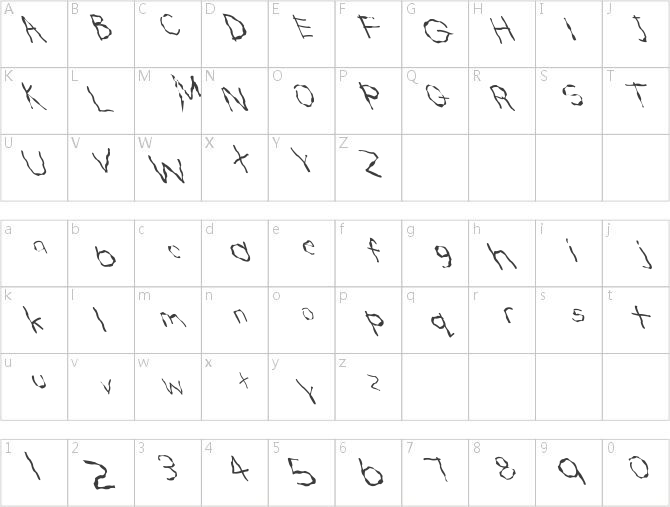
FZ HAND 22 WAVEY LEFTY 詳情頁(yè)
FZ HAND 22 WAVEY LEFTY字體字庫(kù)是一款讓人賞心悅目、百看不厭的英文字體,適合各類(lèi)廣告和產(chǎn)品包裝設(shè)計(jì)應(yīng)用,字體大小0.06MB,格式為ttf字體,上傳用戶(hù)是釜源貿(mào)易,作者/版權(quán)方為未知